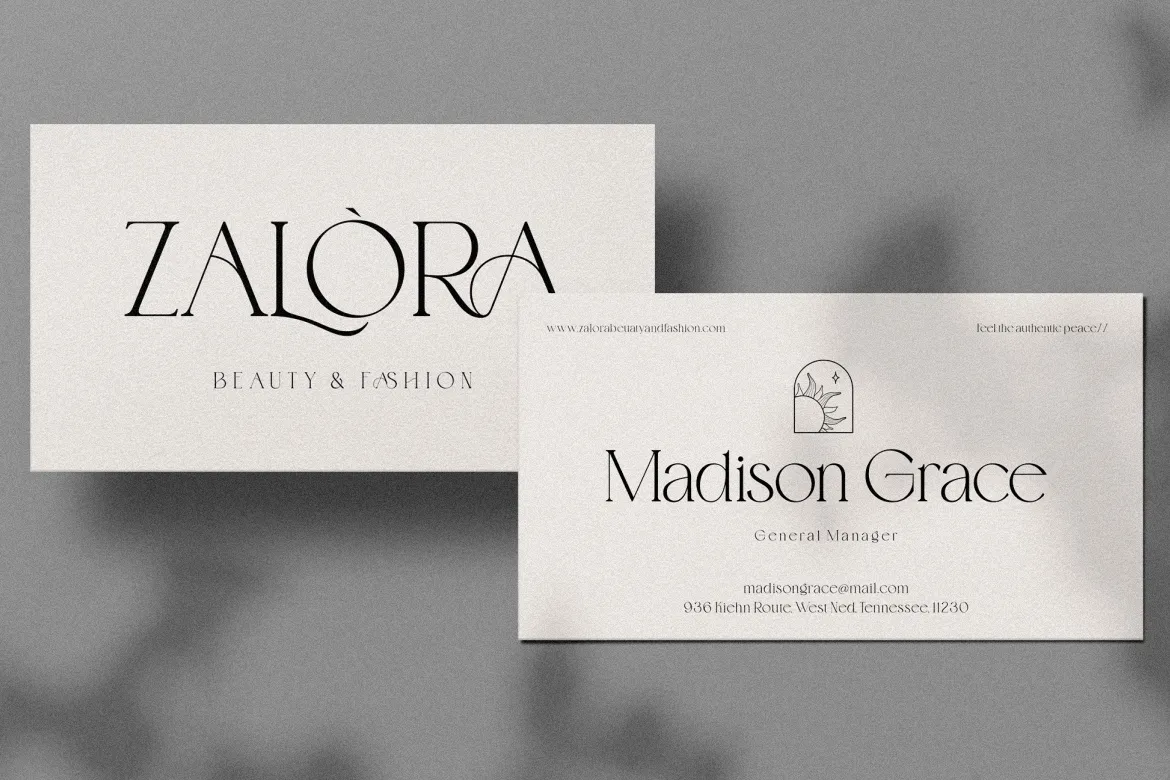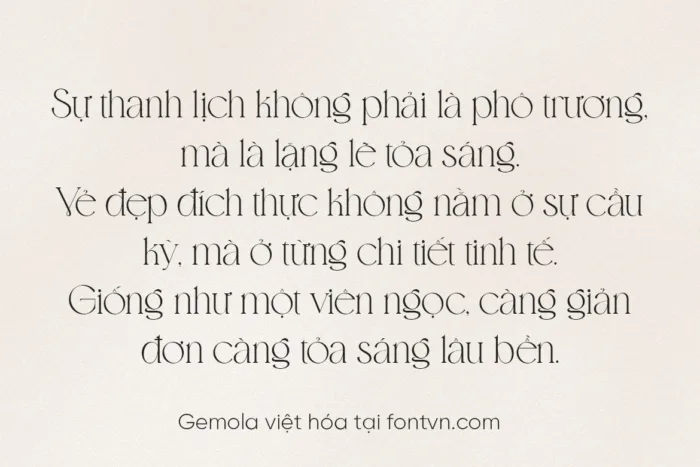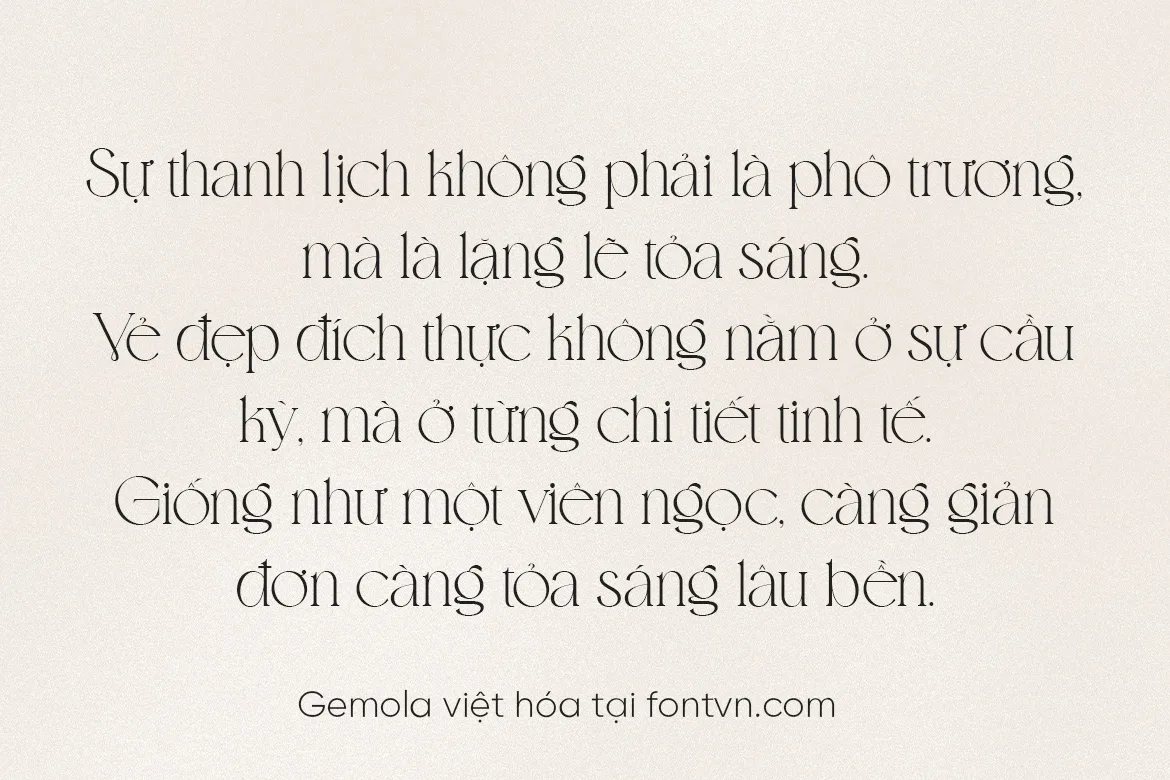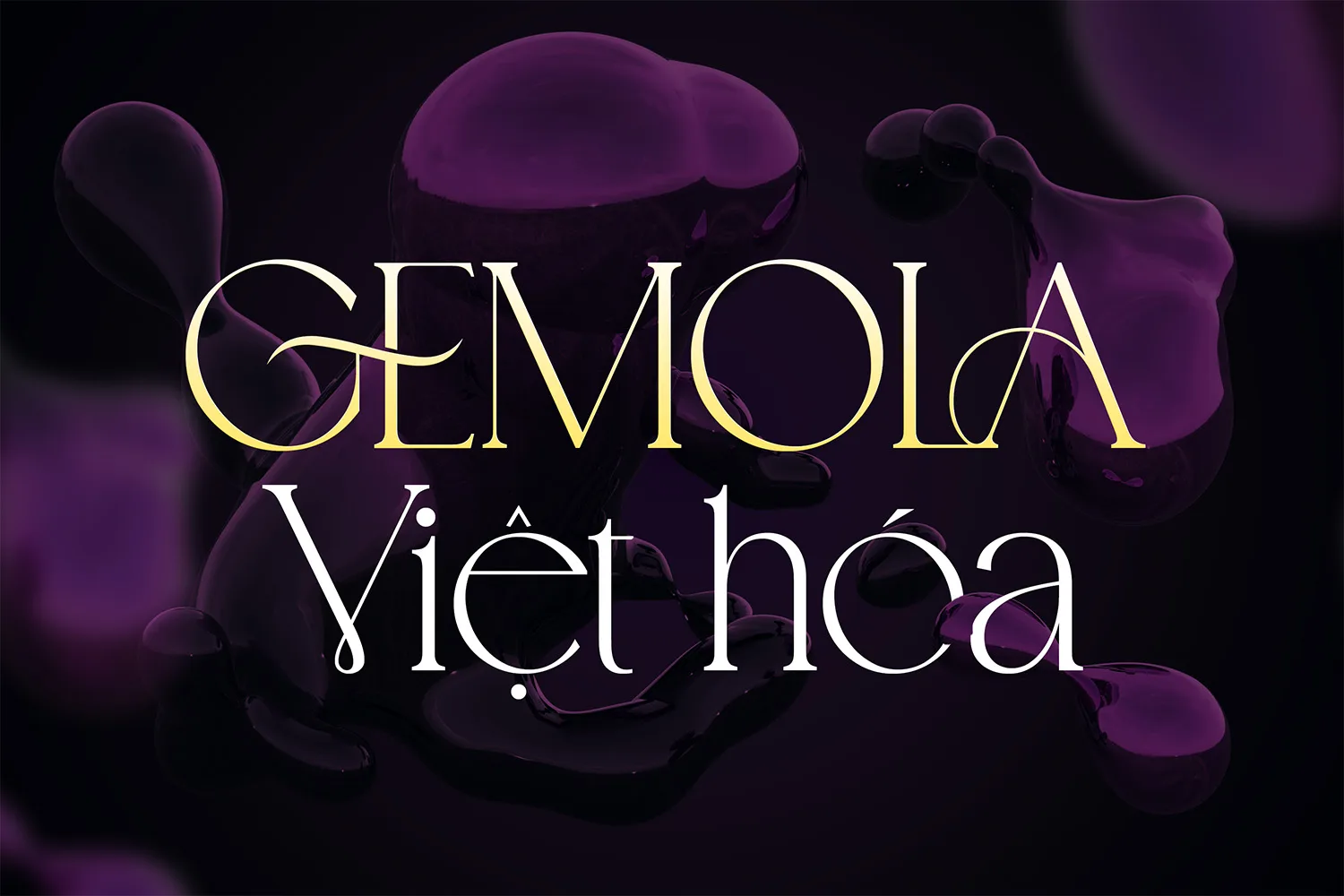
DVN Gemola Việt hóa – Font chữ Cho Thiết Kế Thời Trang & Thương Hiệu Sang Trọng
Gemola Việt hóa là một kiểu chữ serif hiện đại mang phong cách thời thượng với những đường nét thanh mảnh kết hợp chi tiết uốn lượn đầy nghệ thuật. Font sở hữu cảm giác sang trọng, quý phái, phù hợp cho các dự án thiết kế cao cấp như thương hiệu thời trang, mỹ phẩm, trang sức, bìa sách, poster hay bao bì sản phẩm.
Với bộ ký tự tiếng Việt hoàn chỉnh, Gemola giúp bạn dễ dàng ứng dụng trong thiết kế bản địa, giữ nguyên được tinh thần tinh tế của nguyên mẫu nhưng vẫn đảm bảo tính tiện dụng cho người dùng Việt.